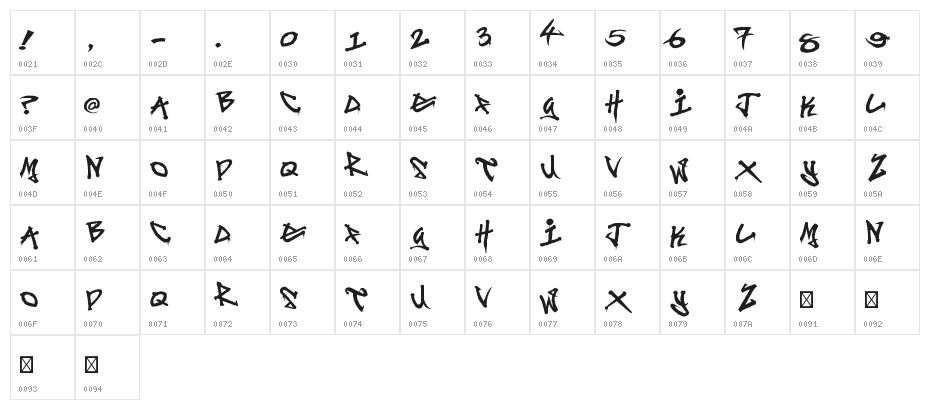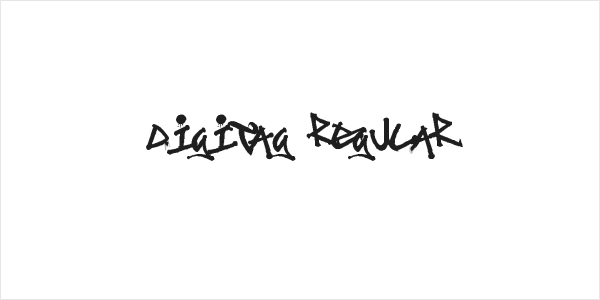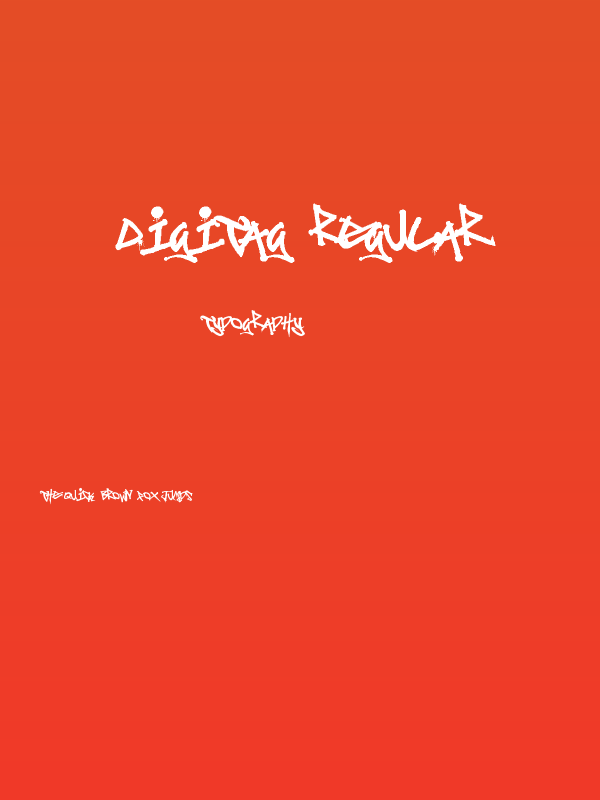
Digitag Regular Font
✎ Drippy
| Stile generale | Urban, Edgy, Graffiti |
| Caso d'uso | Logos, Posters, Album Covers |
| Progetti proposti | Ideal for street art projects, urban-themed designs, music album covers, and edgy branding. |